Tải miễn phí 30 font chữ cực "ngầu" cho website của bạn
Font chữ góp một phần không nhỏ trong hiệu quả thu hút người đọc, bạn đã hiểu font chữ cho trang web ?
Nhiều khi chỉ một điểm nhấn khác biệt so với những sản phẩm thiết kế khác cũng đủ làm bạn nổi bật hơn so với những cái cùng loại. Thiết kế website và thiết kế bộ nhận diện thương hiệu cũng vậy. Internet sẵn sàng cung cấp cho bạn một kho các mẫu chữ đẹp mắt từ miễn phí đến có phí. Sự lựa chọn thuộc về bạn và ngân sách dành cho dự án thiết kế của bạn. Nếu bạn cần một font chữ sành điệu cho website với mức đầu tư tiết kiệm tối ưu, tại sao không chọn trong số 30 font chữ mà chúng tôi mang tới hôm nay? Tại đây có các font chữ miễn phí và có trả phí ở một mức rất hợp lý.
Với các font chữ đặc sắc này, bạn có thể dùng cho cả các ấn phẩm in ấn lẫn sản phẩm online. Chúng có thể dùng làm tiêu đề chính, tiêu đề phụ...làm điểm nhấn cho các thông điệp mà bạn muốn truyền tải. Kích thước, màu sắc của chữ sẽ dễ dàng tùy chỉnh theoo mong muốn của bạn sau khi tải chúng về. Tại đây có cả serif và sans serif font sẵn sàng để đưa vào thiết kế.
Chất lượng của các font đồng đều và đều có sự đầu tư cho từng đường nét để đảm bảo mặt thẩm mỹ và chuyên nghiệp cho sản phẩm mà nó được ứng dụng vào. 30 font chữ được giới thiệu tại đây mang 30 màu sắc và phong cách khác nhau. Bạn có thể chọn một hoặc nhiều hơn một trong số này cho cùng một dự án thiết kế của mình. Sự lựa chọn thông thái là của bạn.
INTRO free font
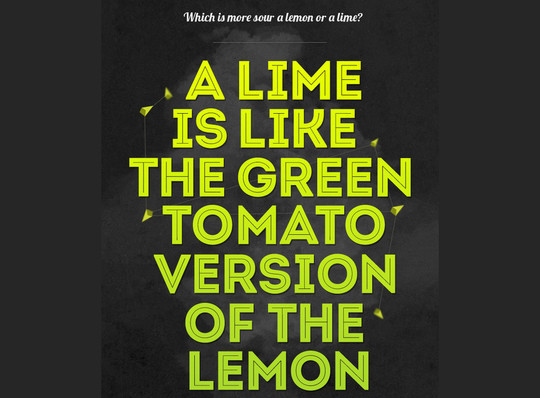
Prosto font (FREE)
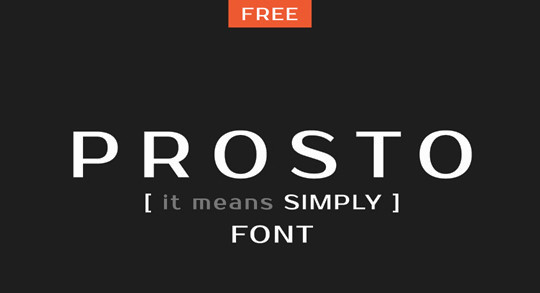
Rex free font
Ribbon
Exo
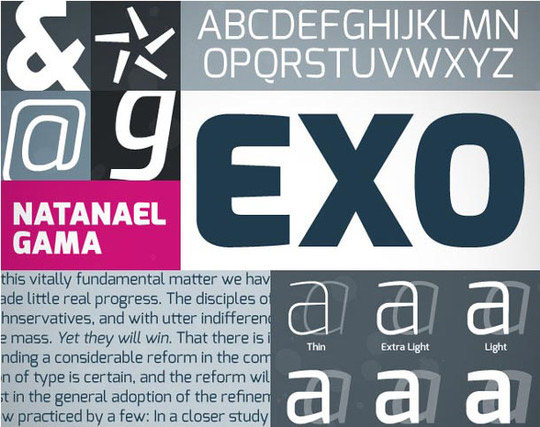
Kilogram
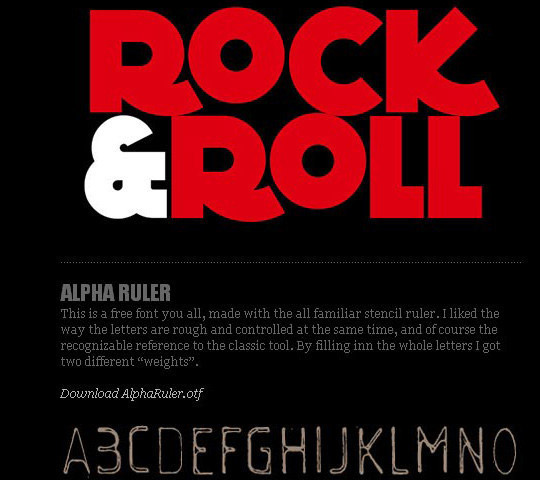
Bready
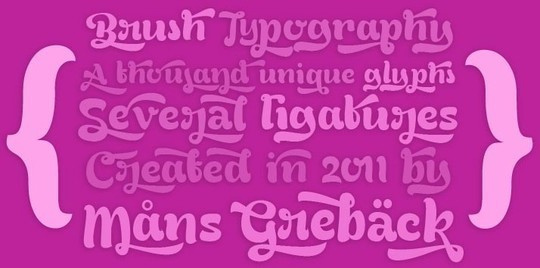
ASO
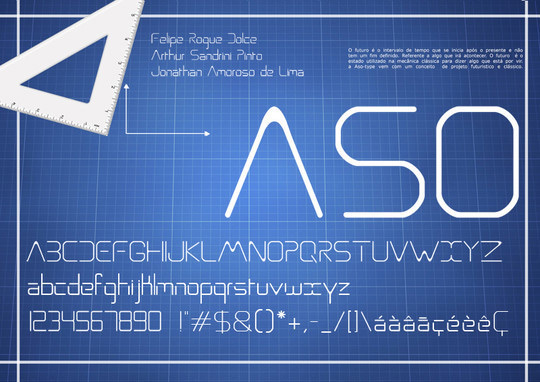
Homestead
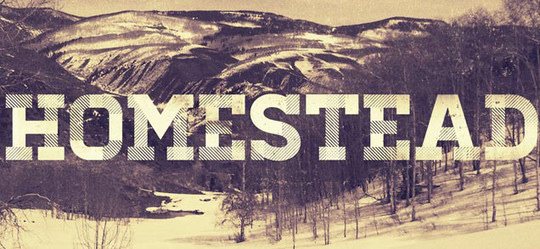
Geotica
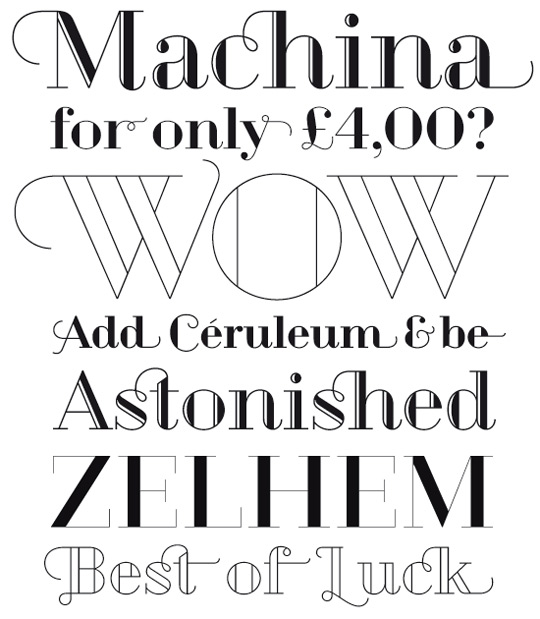
Jura
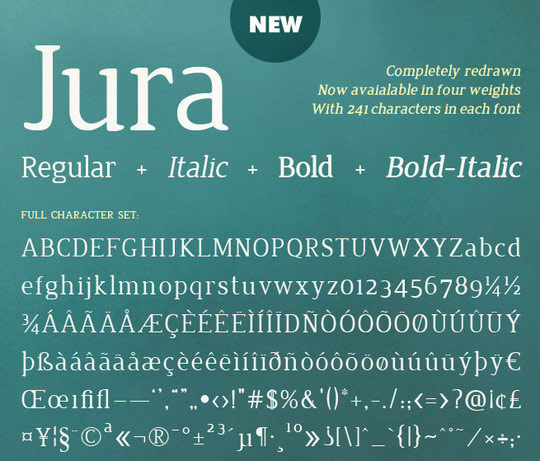
QUB Free Font
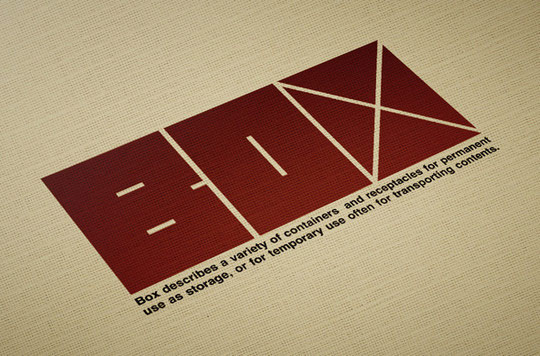
Just Old Fashion
Jembo Hands
Poly – free web font
Carton
Miso
Vastagurly Display
Sn-Blinds
Knubbel
Adamas Regular – Free font
Cubano
DUKE
Ranger
Nevis
Springsteel
Clutchee
AGE
Punchline
Haus Sweet Haus